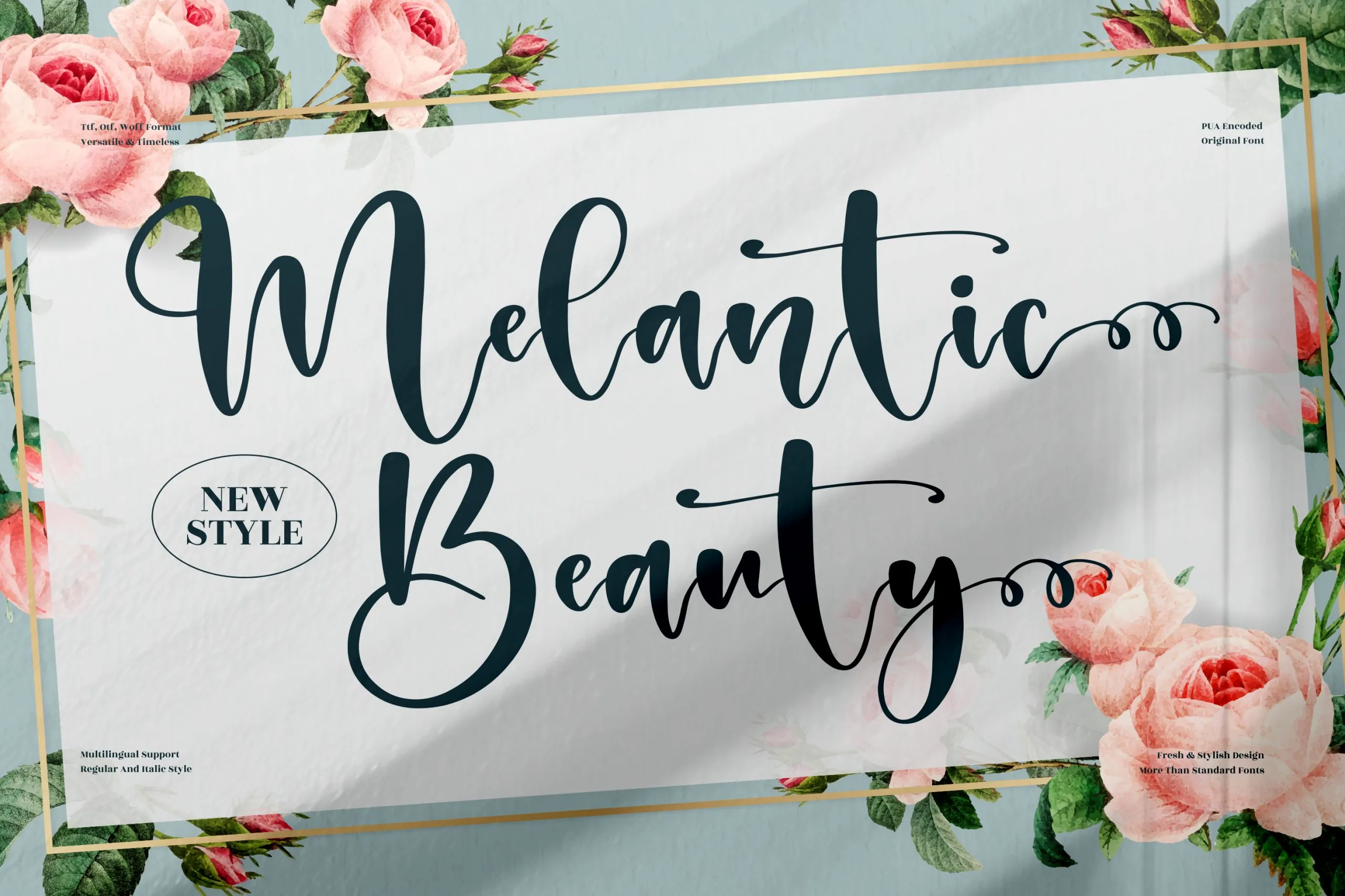
A fonte ‘Melantic Beauty Font’ é uma elegante escolha para projetos que exibem um toque sofisticado e único. Criada pelo designer perspectype, esta fonte é perfeita para projetos de marca, ilustrações, embalagens de produtos, arte digital e design gráfico em geral. Com seu estilo tipográfico artesanal, a ‘Melantic Beauty Font’ permite que você inove em sua identidade visual com uma tipografia verdadeiramente única, deixando um impacto duradouro em seus trabalhos. Neste contexto especial de alta qualidade, ela é perfeita para criações exclusivas como rótulos de embalagens, identidades visuais, selos e materiais promocionais. Seja você designer gráfico ou criativo digital, a ‘Melantic Beauty Font’ oferece uma maneira sofisticada de personalizar qualquer projeto, garantindo um toque único que destacará sua marca.